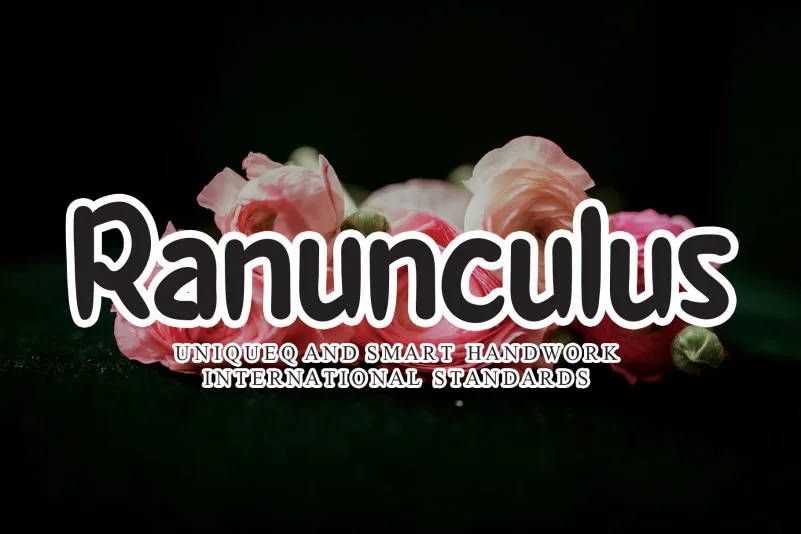
Ranunculus Flower Handwritten Font – Download Grátis
A fonte ‘Ranunculus Flower Handwritten Font’ é uma escolha perfeita para designers que buscam adicionar um toque amigável e natural aos seus projetos. Inspirada no encanto de uma flor ranúncio, essa fonte apresenta um estilo elegante e único, ideal para design gráfico com uma paleta diversificada de opções. A ideia é capturar a essência delicada e suave da natureza em cada letra, criando um visual autêntico que se destaca em diversas aplicações, desde cartões personalizados até websites e aplicativos de design. Com sua elegância e naturalidade únicas, ‘Ranunculus Flower Handwritten Font’ torna-se uma escolha indispensável para designers buscando adicionar uma pitada delicada de artesanato à suas criações digitais.